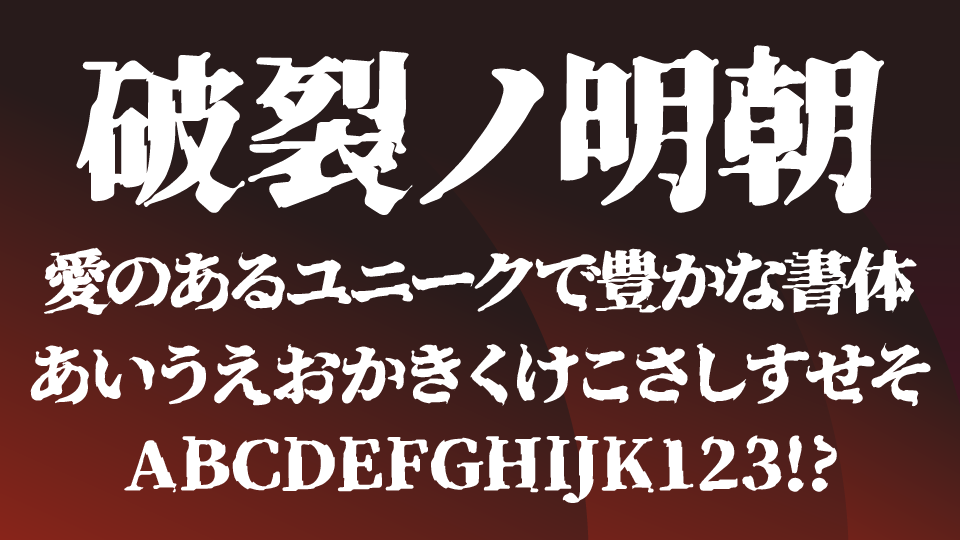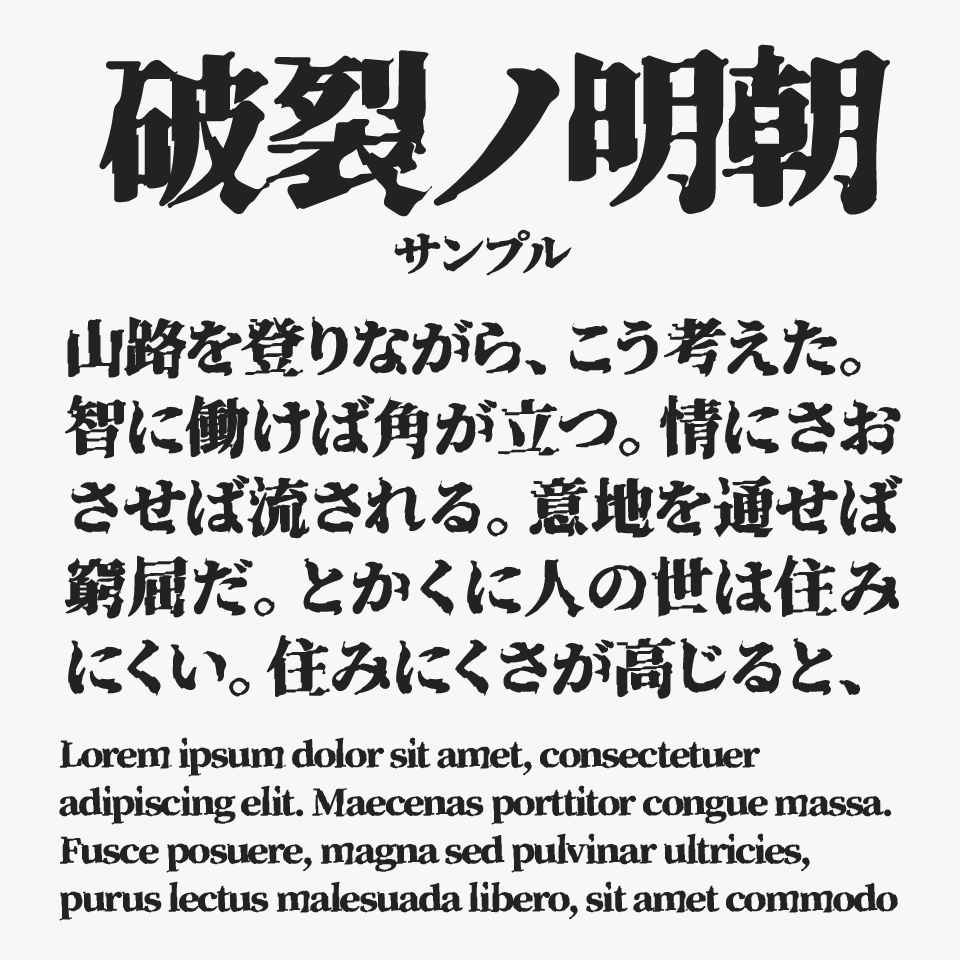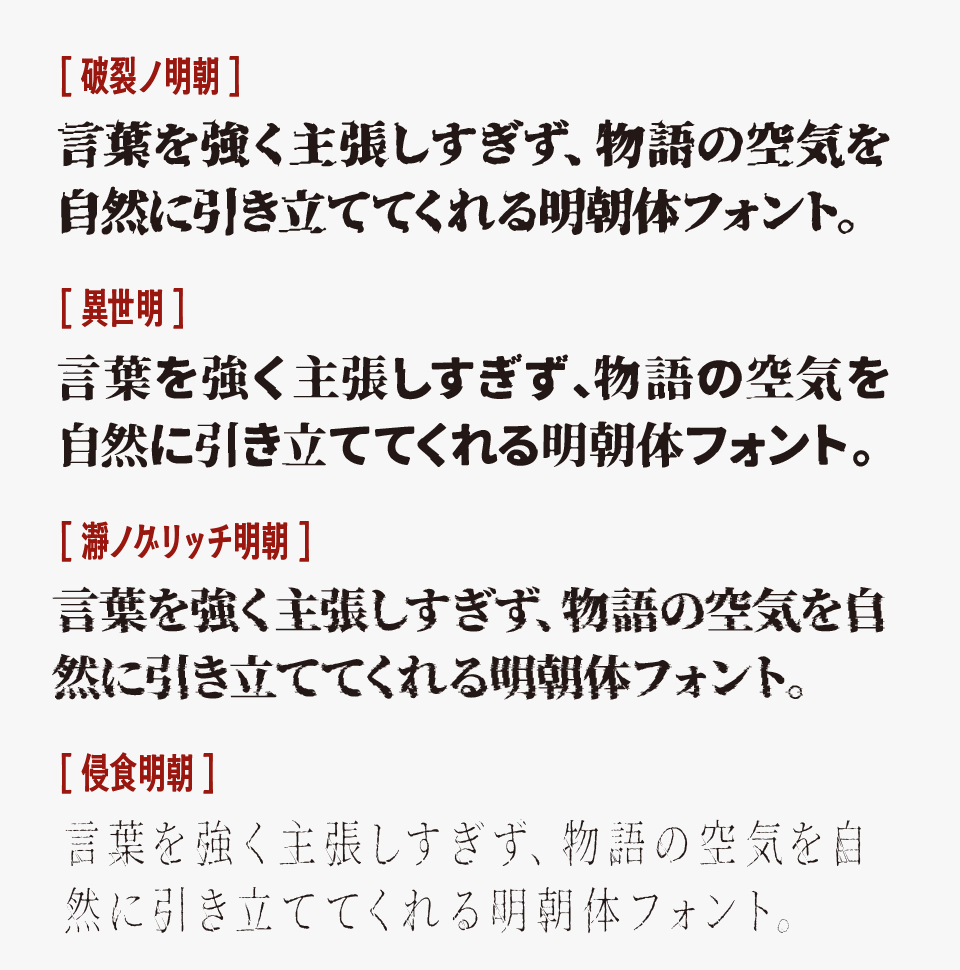
破裂ノ明朝
破裂ノ明朝フォントは、源ノ明朝をベースとして、文字が内側から砕け散ったようなグニャっとした裂け目によって破壊表現を加えたデザイン明朝体フォントです。
太く重厚な骨格と、鋭く飛び散るような割れ加工が組み合わさることで、激しい衝撃や崩壊の瞬間を表現しているようなデザインです。
アクションやダークファンタジー、ホラー作品など、インパクトを重視したデザインにぴったりなフォントです。ベタ打ちのままでも十分インパクトのあるので、タイトルやキービジュアルで使用すれば一瞬で視線を引きつける迫力あるフォントです。崩壊や終末、戦闘、異変といったテーマとも相性が良く、緊張感やドラマ性を際立たせたい場面で存在感を発揮するフォントです。
破裂ノ明朝フォントを、ほかのダイナミックな質感を持つフォントと比較してみると、文字が内側から弾け飛ぶような圧倒的なインパクトが特に魅力です。
比較フォントは、「異世明」「瀞ノグリッチ明朝」「侵食明朝」を使用していますが、どれも特徴的な明朝体フォントなので、ぜひあわせてチェックしてみてください。